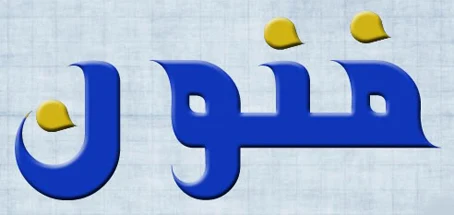
نبذه تعريفيه عن خط قناة فنون هو من أرقى الخطوط العربيه وهو خط يعبر عن منتهى التميز والابداع في الخط العربي
وهو بلا شك من الخطوط المستحب إستخدامها من قبل مصممي الجرافيك المحترفين والمبدعين.
ويعتبر خط قناة فنون من الخطوط التي تضفي لمسه رقي وجمال وأناقه على أي تصميم
ومن مميزات خط قناة فنون أن إدخال مؤثرات الجرافيك عليه تجعله يتألق وتبرز مدى جماله الحقيقي
مما يجعله من الخطوط المعدوده على الأصابع والذي عند إستخدامه بالشكل المناسب والمؤثرات
الابداعيه والاحترافيه تضفي على أي تصميم لمسة جمال وإحترافيه وإبداع .
خط قناة فنون هو من أرقى الخطوط العربيه وهو خط يعبر عن منتهى التميز والابداع في الخط العربي
وهو بلا شك من الخطوط المستحب إستخدامها من قبل مصممي الجرافيك المحترفين والمبدعين.
ويعتبر خط قناة فنون من الخطوط التي تضفي لمسه رقي وجمال وأناقه على أي تصميم
ومن مميزات خط قناة فنون أن إدخال مؤثرات الجرافيك عليه تجعله يتألق وتبرز مدى جماله الحقيقي
مما يجعله من الخطوط المعدوده على الأصابع والذي عند إستخدامه بالشكل المناسب والمؤثرات
الابداعيه والاحترافيه تضفي على أي تصميم لمسة جمال وإحترافيه وإبداع .